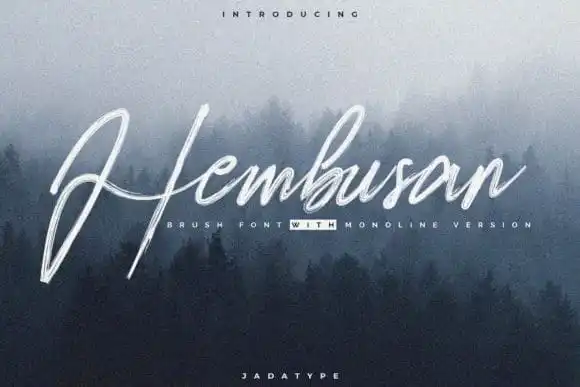
Hembusan Script Font – Download Grátis
Descubra a Hembusan Script Font, uma elegante e vibrante tipografia moderna que irá transformar seus projetos digitais. Esta fonte script é perfeita para quem busca um equilíbrio entre simplicidade e sofisticação. A Hembusan Script oferece um visual orgânico e dinâmico que se adapta a uma variedade de usos, desde cartões de felicitações até headlines de newsletter ou páginas web. Com seu desenho fluido e moderno, esta fonte proporciona não apenas um toque diferente, mas também a garantia de adicionar um ar contemporâneo aos seus projetos. Feita pelo designer jadatype, ela é uma ferramenta versátil que oferece flexibilidade para adaptar ao seu estilo pessoal ou corporativo. A Hembusan Script combina a delicadeza do script com a agressividade da tipografia moderna em um único pacote. Ela se destaca como uma opção excepcional para aqueles desejando inovar e estabelecer sua marca no mercado, garantindo que cada projeto seja reconhecível pela presença única de sua identidade visual. Além disso, a Hembusan Script é perfeita para designers gráficos e profissionais de marketing que buscam expressar os seus ideais visuais em um estilo diferenciado. Este recurso font é uma excelente escolha para quem busca adicionar um toque moderno e único ao seu trabalho ou projeto.